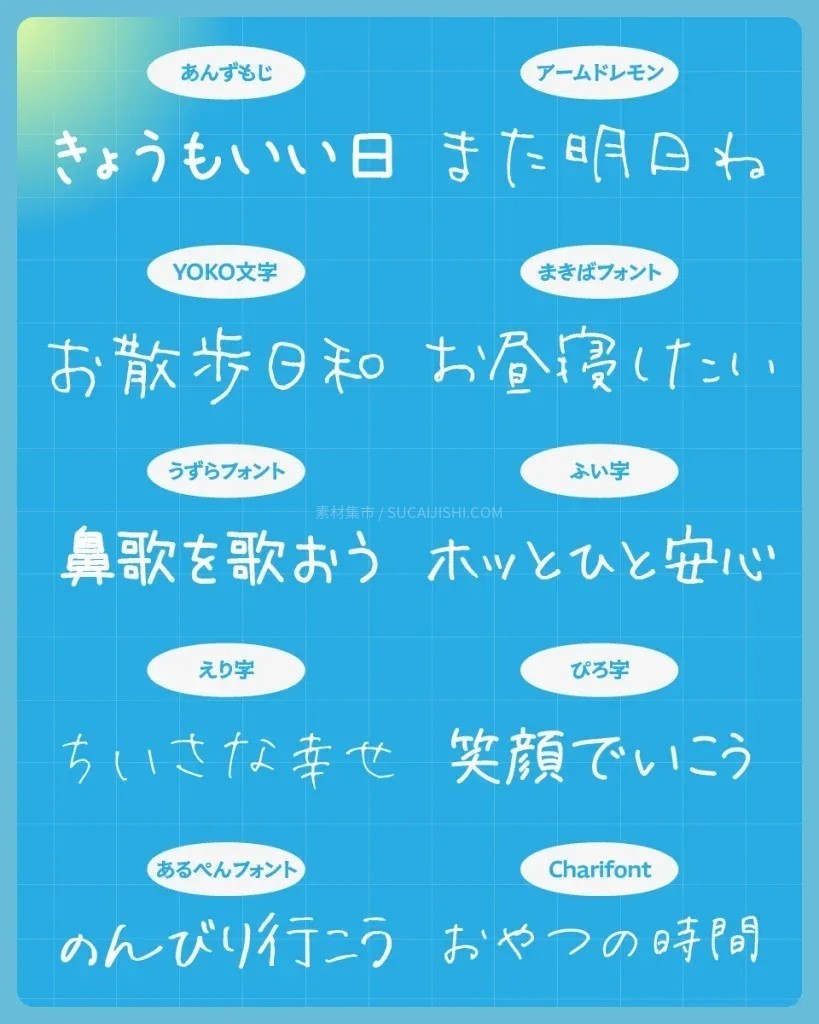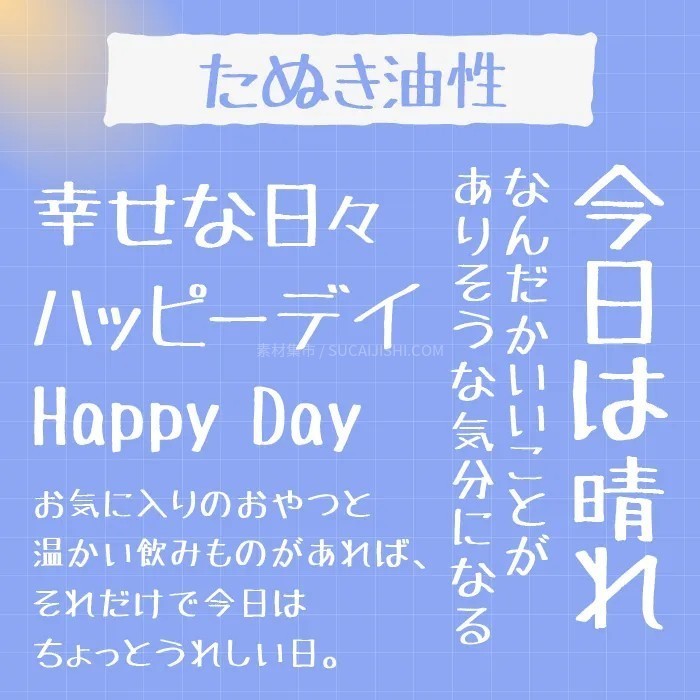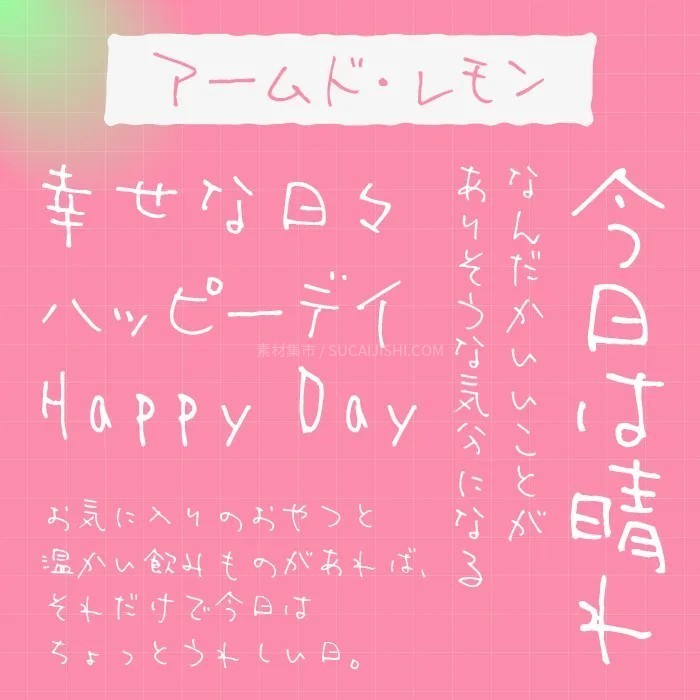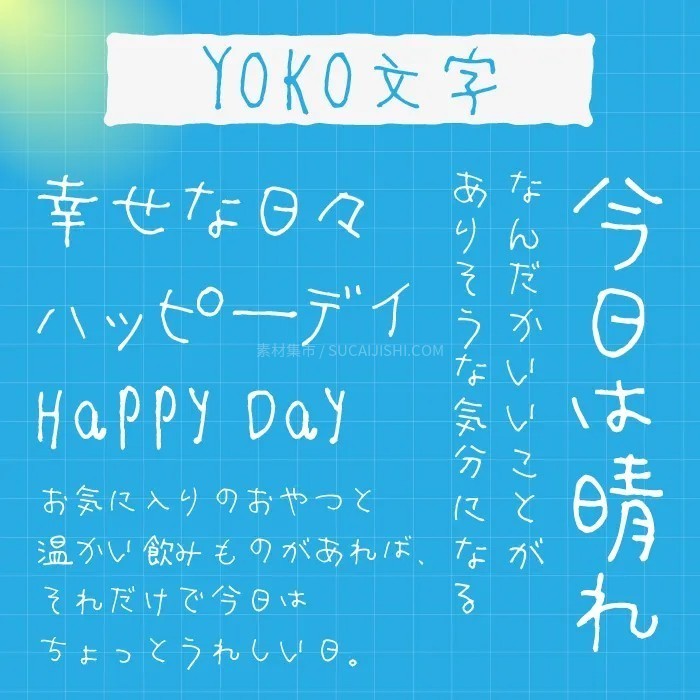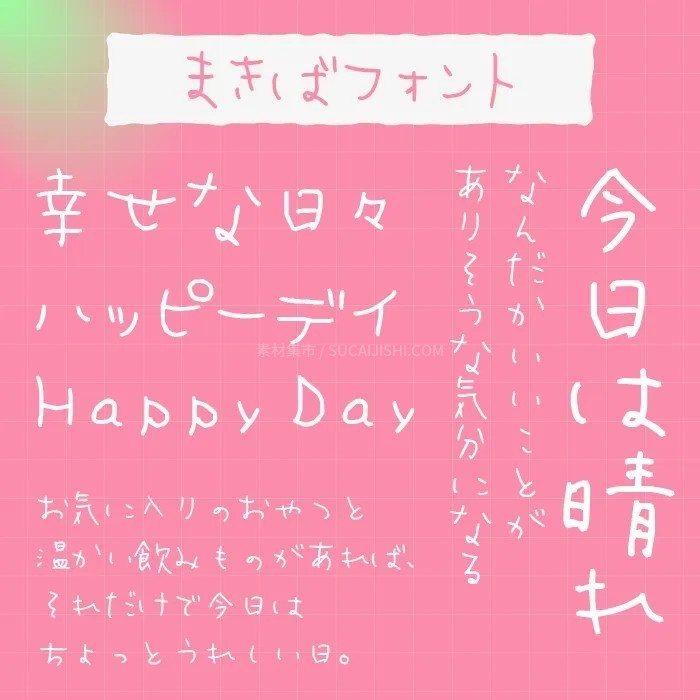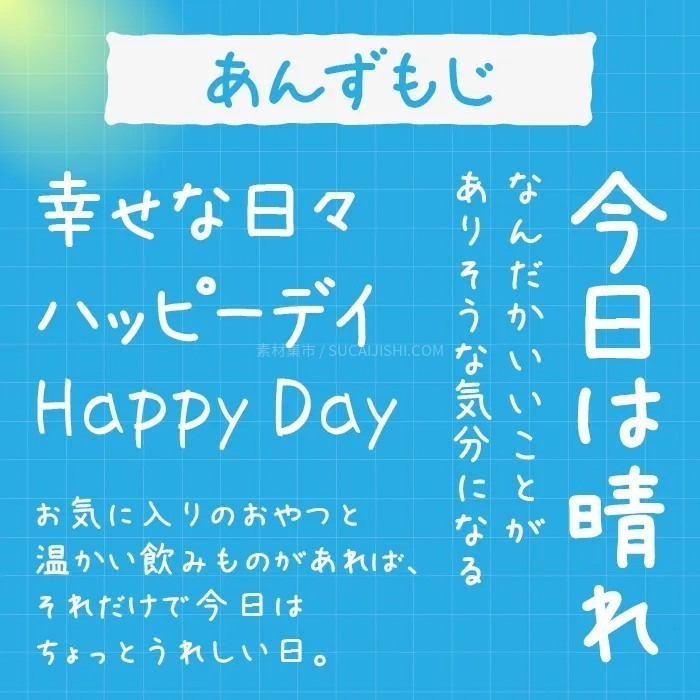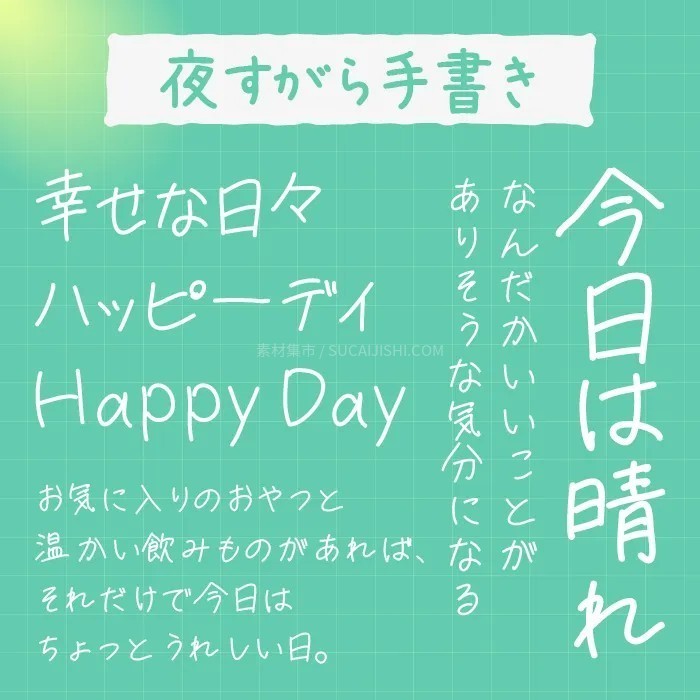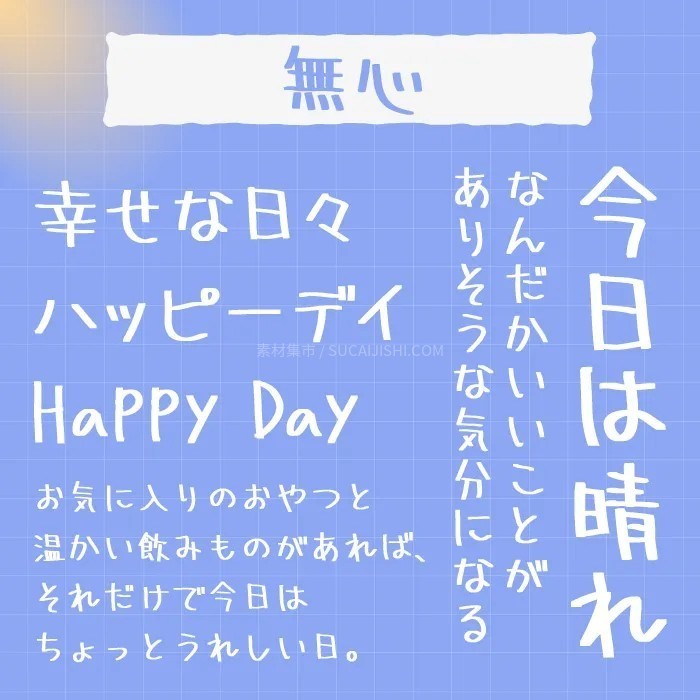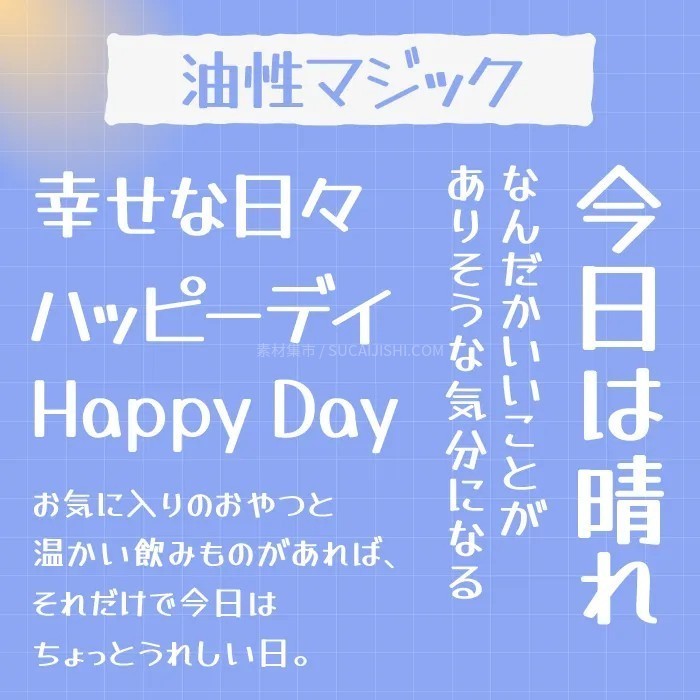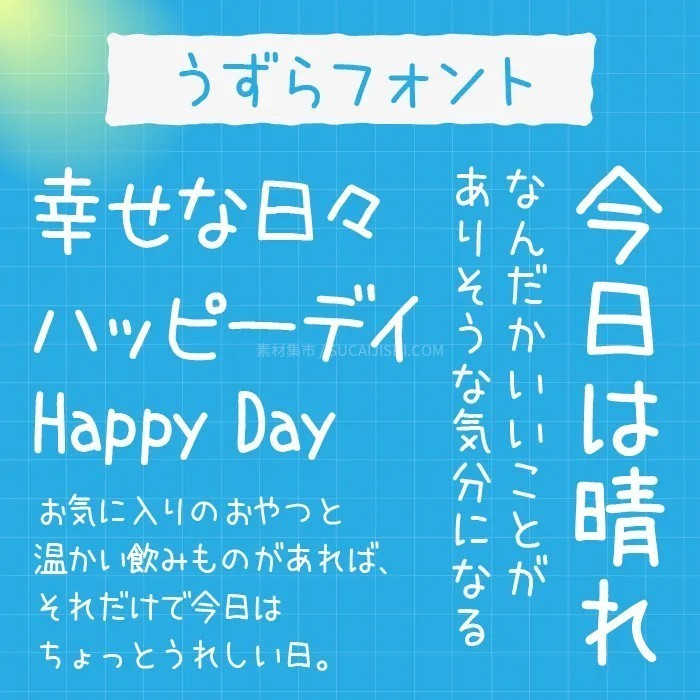
30款可爱的日文手写字体【允许商业用途】
这套精选的30款可爱日文手写字体,字形俏皮生动,充满治愈感与手绘温度。资源全部支持免费商业用途,无论是用于海报设计、包装排版,还是日常社交媒体配图,都能轻松为你的作品注入独特的日系文艺风情,大幅提升设计的视觉亲和力与吸引力。
アームド・レモン
一款独特的手写字体,采用纤细粗糙的线条绘制而成。这些字迹轻松随意,散发着一种质朴的可爱。略带慵懒的气息,拥有独特的魅力,使其有别于典型的圆润笔迹。包含了日语汉字标准第二级以下的汉字。
あんずもじ
一种线条圆润柔和手写字体, 笔压的自然变化和简洁的字母形状传递出一种温暖的气息,令人联想起精心手写的笔记。它在易读性和可爱度之间取得了很好的平衡,使其成为一款适用于各种设计的百搭字体。
夜すがら手書きフォント
一款由作者夜以继日创作的手写字体,风格独特。略微上翘的字母更添韵味,使其成为一款真正能唤起手写感觉的精美字体。包含的汉字是小学六年级所学的汉字。
無心(むしん)
一种手写字体,由作者随意涂鸦而成,没有任何特定的主题或概念。它以强劲而自由的笔触为特色,因为它仅仅是由作者随手写下的文字组成的。 可用于商业用途的字体 这款字体简洁的字形散发着质朴的魅力,自然地传递出手写文字特有的温暖。它用途广泛,从日常信息到亲切的标题,都能轻松驾驭。
YOKO
一款手写字体,其魅力在于简洁质朴的外观,让人联想起随手涂鸦的笔迹。线条粗细和字母倾斜度的自然变化赋予它温暖的手工质感。它唤起一种怀旧和熟悉的感觉,就像你在日记或信件中看到的那样。这款字体非常适合用于带有信息的横幅、强调手工质感的设计以及个人博客。
まきばフォント
这款手写字体,外观令人印象深刻,仿佛字迹自由奔放、不受拘束地书写而成。起伏的线条和独特的字母形状营造出一种简洁的田园氛围。它的不完美之处反而赋予它一种温暖感,使之成为一种令人感到舒适的字体。
たぬき油性マジック
一款手写字体,其魅力在于其自然的线条,仿佛是用马克笔轻轻书写而成。 适中的字重和简洁的字形设计赏心悦目,营造出一种不做作的可爱感。同时,良好的易读性也保证了这款字体的实用性,使其成为一款用途广泛的字体,从标题到正文均可胜任。
851マカポップ
一款免费的手写字体,风格粗犷,笔触粗犷,类似马克笔。它是一款流畅自然的马克笔手写字体。 这款字体活力十足,尤其擅长表达趣味和欢快之感。它非常适合营造活泼氛围的场合,例如活动公告或儿童设计。
うずらフォント
一款极具吸引力的字体,它拥有柔和圆润的形状和自然的手写感。 它给人一种朴实无华、平易近人的感觉,仿佛收到一张悄悄留下的手写便条,倍感温暖。推荐给所有正在寻找可爱易读手写字体的人。 这款字体非常适合用于信函风格的设计、社交媒体帖子以及展示手工工艺品。它完美地捕捉到了手写文字温暖而富有感染力的感觉。
アオハルマーカーmini
一款手写字体,唤起人们对青春时期在笔记本上涂鸦的清新感觉。 字体介绍文章 这款字体线条纤细轻盈,给人一种转瞬即逝的感觉。它非常适合学生主题设计和情感丰富的视觉作品。 目前该版本不包含汉字,但计划在未来的更新中发布包含汉字的正式版本。我很期待。
油性マジック(Yusei Magic)
一种独特的手写字体,使用粗油性马克笔绘制而成,每个字符都适合放在一个正方形内。 可用于商业用途的字体 在为超市及类似商店设计流行风格图案时,或许可以尝试运用这种方法。当然,您也可以将其融入横幅、醒目的标题和其他突出文字中,打造吸睛的设计。30款可爱的日文手写字体【允许商业用途】
しろくまフォント
一款手写字体,“灵感源自北极熊的爪印”。 它给人一种温柔平静的感觉,营造出一种温暖的氛围,让人联想起绘本和手工制品。这是一款易于使用的字体,兼具可爱与易读性。
kawaii手書き文字
经典的手写字体,其特点是线条圆润、字母形状简洁。这款字体给人一种亲切迷人的感觉,因此用途广泛,从标题到正文都适用。它能轻松展现手写文字的温暖质感。
左利きの彼女
字体采用由左撇子艺术家精心创作的女性化手写体,呈现出非常美丽迷人的手写风格。 可用于商业用途的字体 提供两个版本:免费版和标准版。免费版包含平假名、片假名、字母数字字符以及适合小学三年级学生使用的字符。标准版售价1000日元,包含JIS第一标准中的约2950个汉字以及314个新增字符。
全員集合!ポップ体
Pop字体是一种迷人的手写字体,看起来像是充满活力的孩子画的。线条的轻微弯曲和字母略微不平衡的构图营造出一种明亮而质朴的氛围。它兼具流行字体特有的俏皮感和手工质感,让人只需看一眼就能心情愉悦。
藍原サインペン
字体的魅力在于其轻盈飘逸的笔触,仿佛是用马克笔书写一般。自然流畅、略带瑕疵的线条赏心悦目,给人一种亲切熟悉的感觉,让人联想起笔记或日记。其简洁而温暖的风格使其成为一款用途广泛的字体,能够轻松融入各种设计风格。
エビハラのくせ字
独特的手写字体充分展现了每个字符笔迹的独特特征。 字母略带瑕疵的质感正是它的魅力所在,赋予字体一种只有手写体才能带来的真实温暖感。这种字体在注重日常生活感和亲切感的设计中尤为突出。字体设计精美绝伦,笔触如圆珠笔般晕染开来,情感饱满动人。
ふい字
这款字体逼真地再现了笔压和字母的流畅度,给人一种亲切友好的感觉,仿佛是手写的便条。它散发着柔和的气息,是一款经久不衰的经典手写字体。
手書き雑フォント
这款手写体字体笔触粗犷,散发着阳刚、个性十足又不失休闲的气息,如同手写笔记一般,给人一种轻松迷人的感觉。刻意营造的粗犷感赋予了它其他字体所不具备的独特个性。据说它支持多种语言,包括手写字体中罕见的 JIS 3 级及以上汉字,以及埃塞俄比亚语、越南语、希腊语、亚美尼亚语、希伯来语、泰语、中文(几乎)、韩语(部分)和缅甸语(无法正确显示,仅包含一部分)。   30款可爱的日文手写字体【允许商业用途】
紬フォント
一种将略带圆润的字符与自然的手写感相结合的字体。 柔和流畅的线条赏心悦目,营造出平静柔和的氛围。它既可爱又沉稳,因此很容易融入各种设计风格,从杂货到咖啡馆风格的设计都适用。